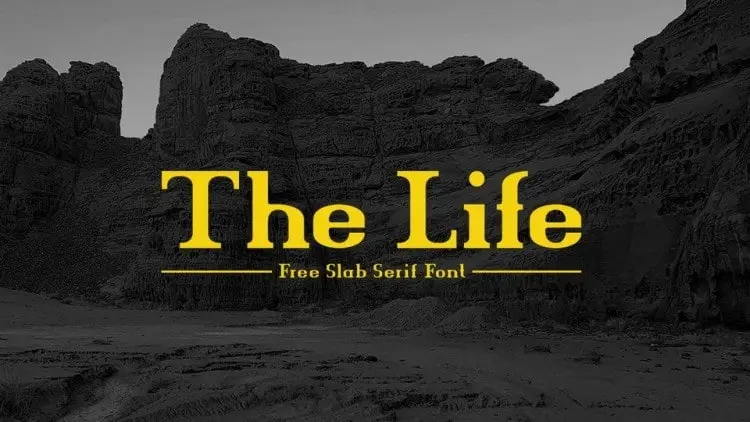
The Life Serif Font – Download Grátis
A The Life Serif Font é uma tipografia serifada projetada para diversos usos. Suas curvas quentes e contrastes altos combinam perfeitamente com os finos e estilizados contornos serifados, fazendo do texto um destaque imediato e elegante. Perfeita para aplicações de exibição como banners, selos, outdoors e capas, a The Life Serif Font é o ideal para transformar qualquer projeto em algo marcante e visualmente atraente. Seu design permite que os editores criem texturas únicas e impactantes, mantendo-se fiel à elegância dos títulos serifados ao mesmo tempo em que oferece um contraste vibrante que se adapta perfeitamente para um amplo leque de projetos gráficos.